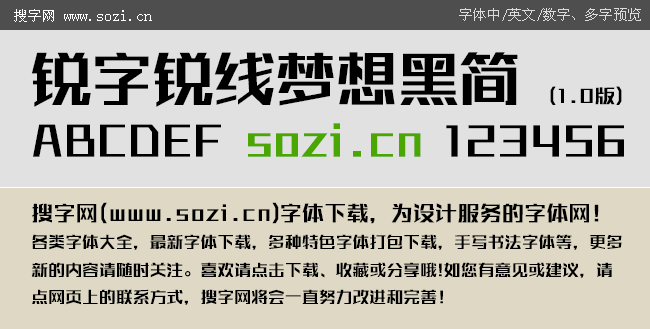
銳字銳線夢想黑簡V1.0
搜字網(wǎng)提供一款銳字銳線夢想黑簡V1.0中文字體下載,銳字銳線夢想黑簡是一款以黑體字為原型,進(jìn)行了新的藝術(shù)設(shè)計的藝術(shù)字體,適合應(yīng)用于廣告設(shè)計、名片設(shè)計、包裝印刷、產(chǎn)品設(shè)計等應(yīng)用。